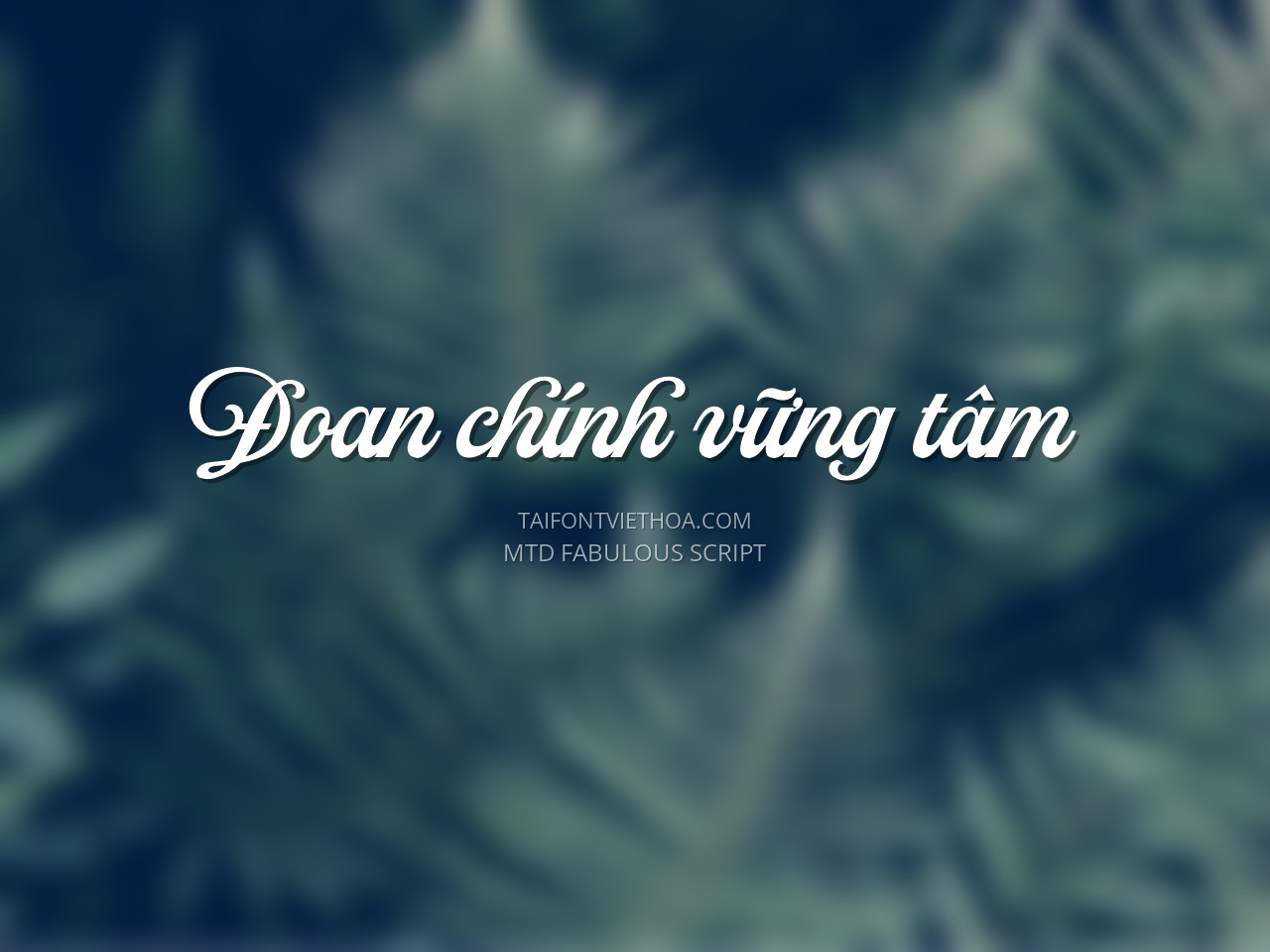
Tác giả Font: Maximiliano R. Sproviero
Giới thiệu về font Fabulous Script
Fabulous Script là một font chữ viết tay sang trọng, uyển chuyển và đậm chất nghệ thuật, được thiết kế bởi Motokiwo Type (MTD). Lấy cảm hứng từ những nét thư pháp hiện đại và phong cách viết tay thanh lịch, font mang đến vẻ đẹp mềm mại nhưng không kém phần sắc sảo, hoàn hảo cho các thiết kế cao cấp hoặc mang yếu tố cảm xúc. Phiên bản Việt hóa được MTD trực tiếp thực hiện, hỗ trợ đầy đủ tiếng Việt và hơn 70 ngôn ngữ khác, cho phép bạn dễ dàng áp dụng trong các thiết kế đa ngôn ngữ mà vẫn giữ được tính thẩm mỹ và hài hòa.
Đặc điểm thiết kế và ứng dụng của font Fabulous Script
Fabulous Script có độ nghiêng nhẹ, đường cong mượt mà và kết cấu chữ thanh thoát. Những ligatures được chăm chút tỉ mỉ cùng với các ký tự thay thế (alternates) mang lại trải nghiệm trình bày chữ viết tay hoàn toàn linh hoạt và sinh động. Font đặc biệt phù hợp với các thiết kế đòi hỏi yếu tố nghệ thuật và cá nhân hóa.
Ứng dụng lý tưởng: thiết kế thiệp cưới, thiệp mời sự kiện, logo thương hiệu cá nhân, tiêu đề blog thời trang, bìa sách sáng tạo, bao bì mỹ phẩm, hoặc các bài đăng mạng xã hội. Ngành nghề phù hợp: wedding planner, studio ảnh nghệ thuật, thương hiệu làm đẹp, quà tặng cá nhân, thiết kế handmade, và các dự án truyền tải cảm xúc cá nhân.